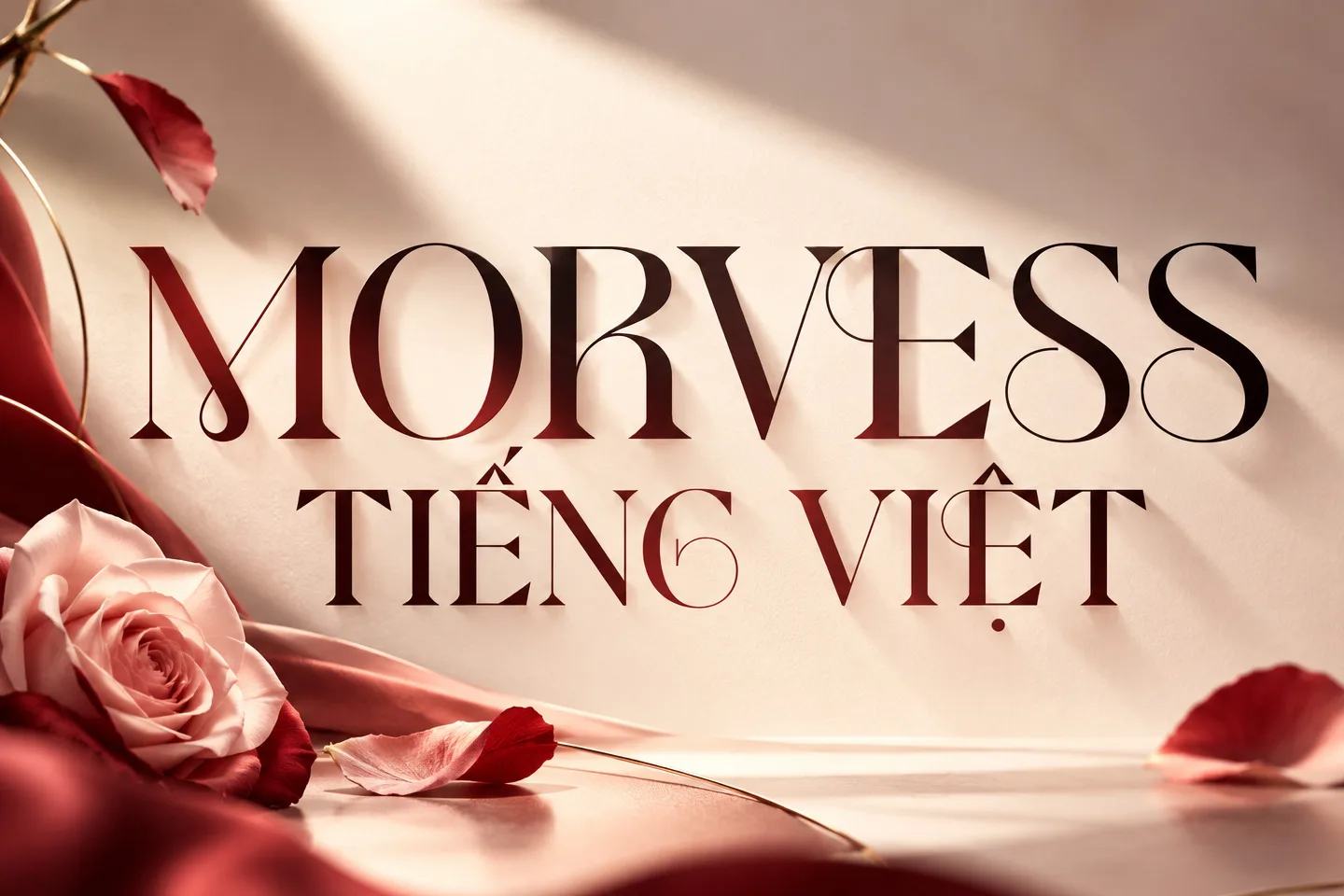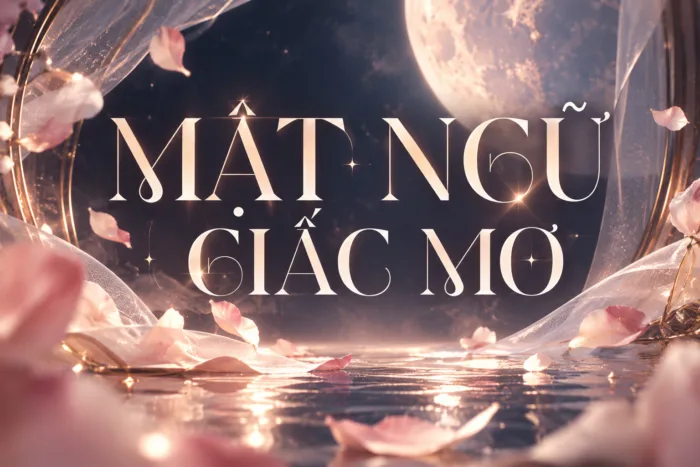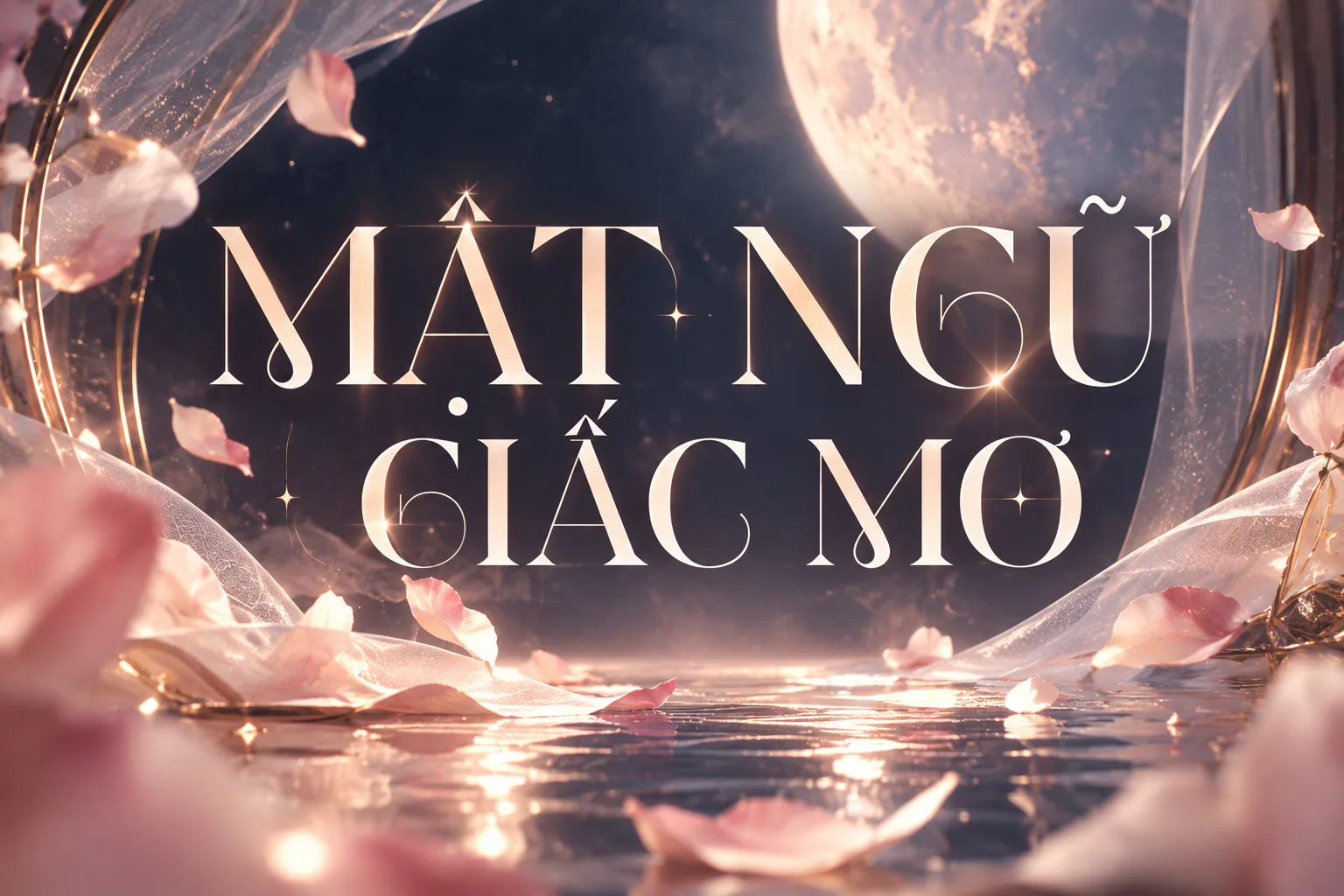
DVN MORVESS tiếng Việt – Font Serif Sang Trọng Mang Đậm Chất Thời Trang
DVN MORVESS là kiểu chữ serif tương phản cao mang tinh thần thời trang, thanh lịch và đầy tính nghệ thuật. Những đường nét mảnh – dày được xử lý rõ rệt, kết hợp với các chân chữ sắc gọn tạo nên vẻ ngoài sang trọng, có chiều sâu và đặc biệt nổi bật khi sử dụng ở kích thước lớn.
Font phù hợp với các thiết kế cần cảm giác cao cấp và editorial như logo thương hiệu, thời trang, mỹ phẩm, tạp chí, poster, tiêu đề, bìa sách và các ấn phẩm quảng cáo. Hình dáng chữ mang hơi hướng cổ điển nhưng được tiết chế theo ngôn ngữ hiện đại, giúp DVN MORVESS dễ dàng tạo điểm nhấn thị giác mà không cần quá nhiều yếu tố trang trí.